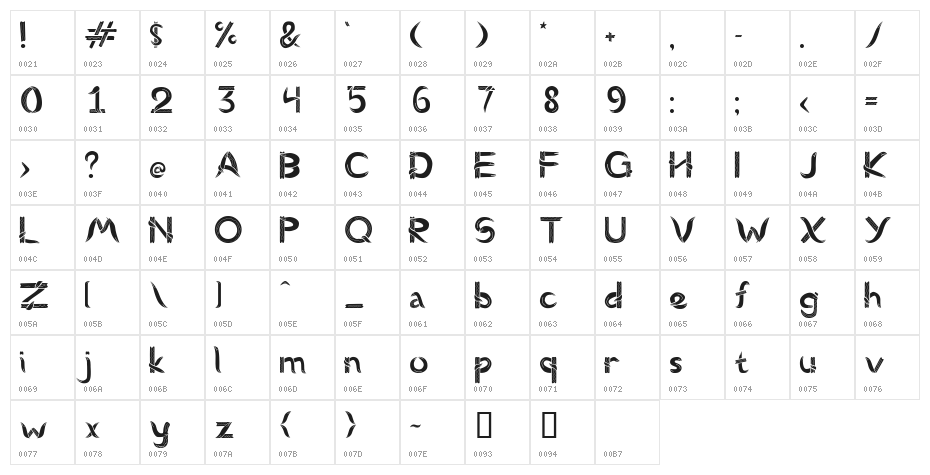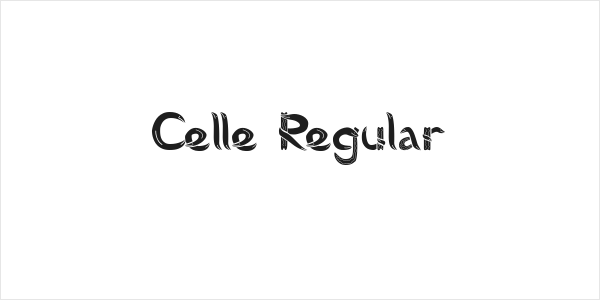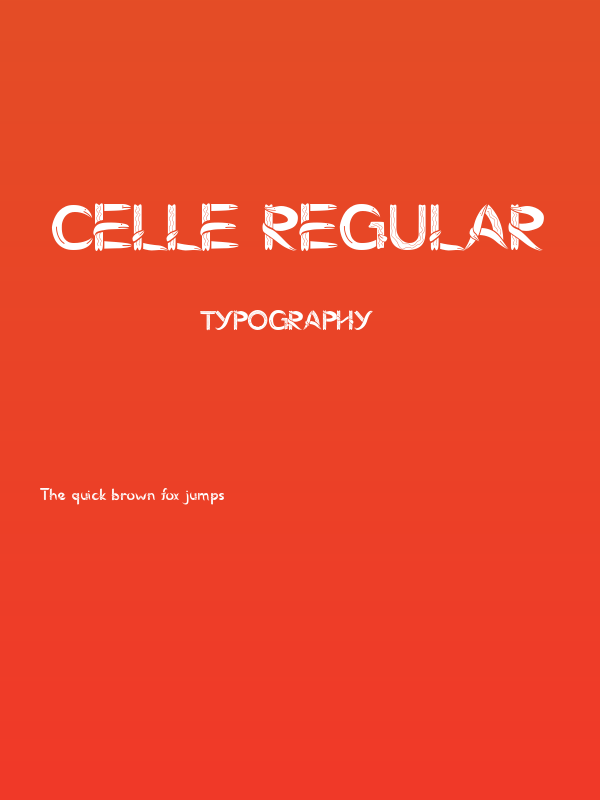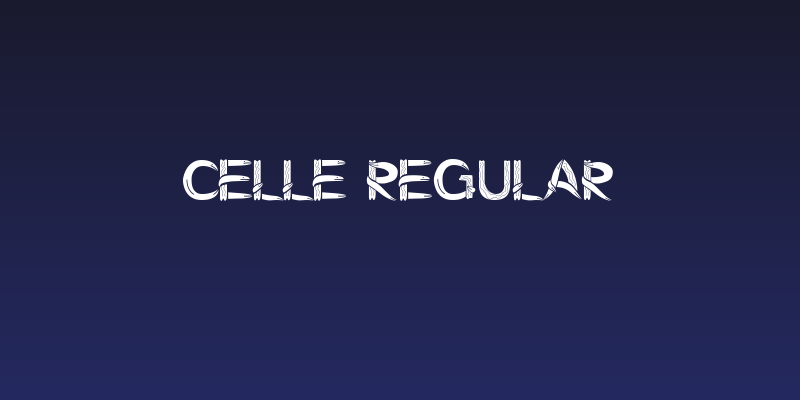
Celle Regular Font
| Gesamtstil | Artistic, Modern |
| Vorgeschlagene Projekte | Ideal for branding, posters, album covers, and artistic projects that require a bold and expressive typeface. |